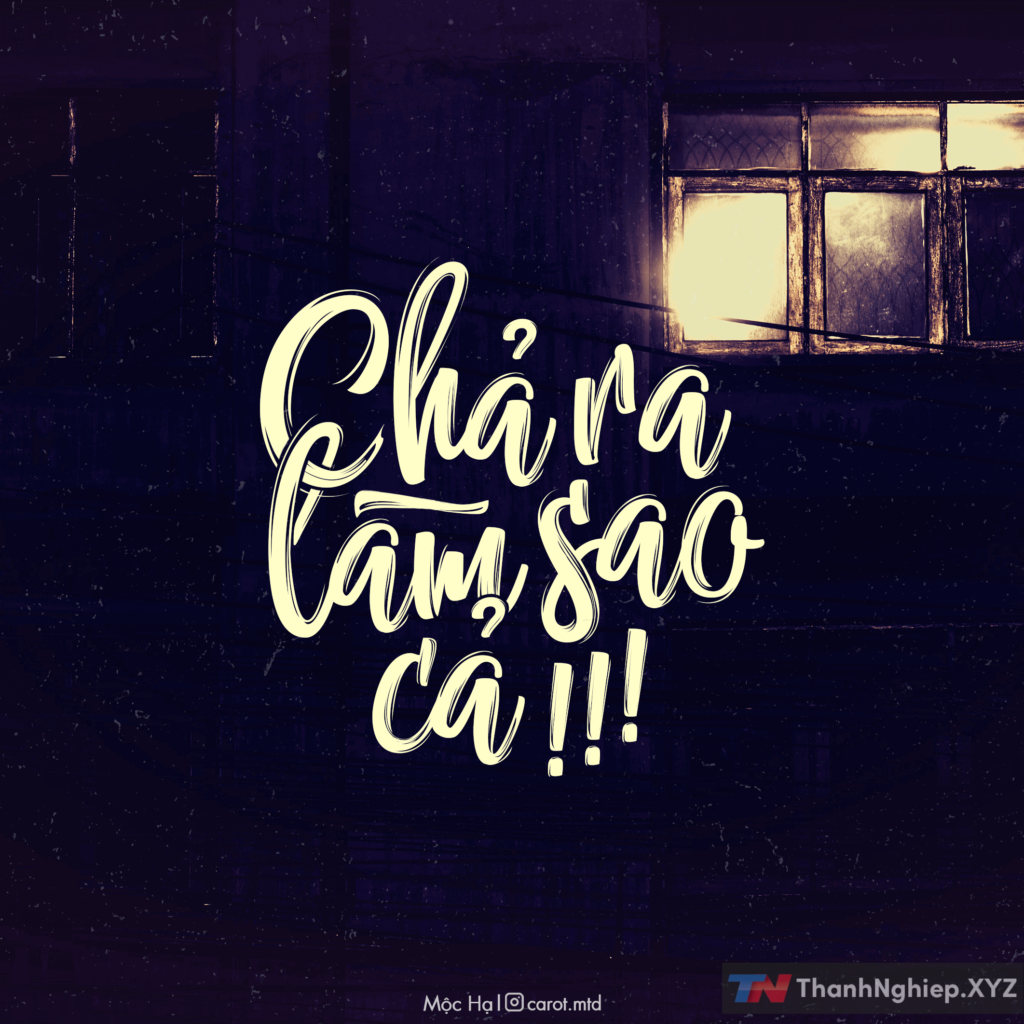
29 FONT MTD VIỆT HÓA (P2) – Font dùng làm Typography, Video
Nếu bạn là người làm thiết kế, dựng video, làm thumbnail YouTube hay đơn giản là yêu thích nghệ thuật chữ đẹp thì chắc chắn không nên bỏ qua bộ sưu tập 29 Font Việt Hóa MTD (Phần 2) được chia sẻ miễn phí bởi Mộc Hạ – một cái tên quen thuộc trong cộng đồng Việt hóa font chữ.
Đây không chỉ là những font thông thường, mà là những kiểu chữ được chọn lọc kỹ lưỡng, đa dạng phong cách – từ thư pháp, cổ điển, viết tay cho đến hiện đại, phá cách. Đặc biệt, toàn bộ font trong bộ này đều đã được Việt hóa cẩn thận, chuẩn dấu tiếng Việt, đồng thời đã sửa lỗi cài đặt, đổi lại tên font dễ nhớ – dễ tìm, giúp bạn thao tác dễ dàng hơn trong các phần mềm như Photoshop, Premiere, Canva, v.v.
✅ Những Điểm Nổi Bật Của Bộ Font MTD (P2)
• Việt hóa đầy đủ dấu và ký tự tiếng Việt, không bị lỗi hiển thị
• Đổi tên font dễ nhớ, thuận tiện tìm kiếm trong hệ thống
• Đa dạng thể loại, từ font script viết tay đến sans-serif hiện đại
• Tương thích tốt với nhiều phần mềm thiết kế và dựng phim
💡 Gợi Ý Sử Dụng
• Typography video âm nhạc: Các font như Lazy Ride, Loveletter No.9, Daytonia sẽ giúp bạn tạo những đoạn text đẹp mắt, cảm xúc.
• Banner – Poster quảng cáo: Retrology Block hoặc Prida 01 Bold cực kỳ phù hợp để tạo điểm nhấn tiêu đề.
• Thumbnail YouTube: Font script nghệ thuật như Charlize One hay Hangbird giúp thumbnail trở nên nổi bật và ấn tượng.
• Trích dẫn truyền cảm hứng (quote): Kết hợp các font viết tay như Mind Blowing Light hay Maryatha để truyền tải cảm xúc mượt mà hơn.
Danh sách font trong bộ 29 FONT MTD VIỆT HÓA (P2) này:
• MTD Abbassy Script
• MTD Acryle Script
• MTD AlFresco
• MTD Anydore
• MTD Authentica Rough
• MTD Berliana Monoline
• MTD Carrington
• MTD Charlize One
• MTD Daytonia
• MTD Elodie
• MTD Hangbird
• MTD Hijrnotes
• MTD Himalaya Sans Serif
• MTD Himalaya
• MTD Houstoner Script
• MTD JV Signature Regular
• MTD Lazy Ride Script
• MTD Loveletter No.9
• MTD Maryatha
• MTD Mind Blowing Light
• MTD Nettizen Script Dancing
• MTD One Starry Night
• MTD Portrait Script Bounce
• MTD Prida 01 Black
• MTD Prida 01 Bold
• MTD Prida 01 Light
• MTD Prida 01
• MTD Prida 02 Calt
• MTD Retrology Block
Bên dưới là một số ảnh demo của font:
29 FONT MTD VIỆT HÓA (P2) - Font dùng làm Typography, Video - 1
MTD Berliana Monoline
29 FONT MTD VIỆT HÓA (P2) - Font dùng làm Typography, Video - 2
MTD Charlize One
29 FONT MTD VIỆT HÓA (P2) - Font dùng làm Typography, Video - 3
MTD Hijrnotes
29 FONT MTD VIỆT HÓA (P2) - Font dùng làm Typography, Video - 4
MTD Houstoner Script
29 FONT MTD VIỆT HÓA (P2) - Font dùng làm Typography, Video - 5
MTD Lazy Ride Script
29 FONT MTD VIỆT HÓA (P2) - Font dùng làm Typography, Video - 6
MTD Mind Blowing Light
29 FONT MTD VIỆT HÓA (P2) - Font dùng làm Typography, Video - 7
MTD Nettizen Script Dancing